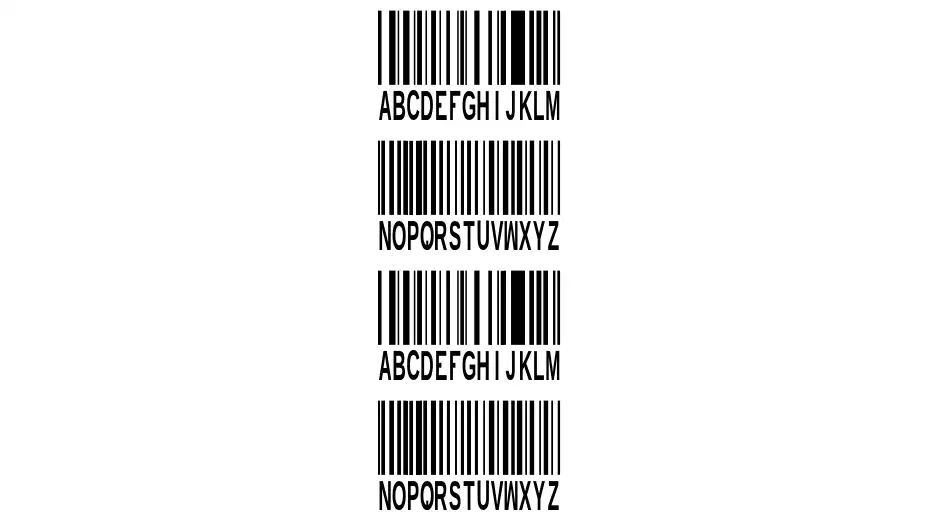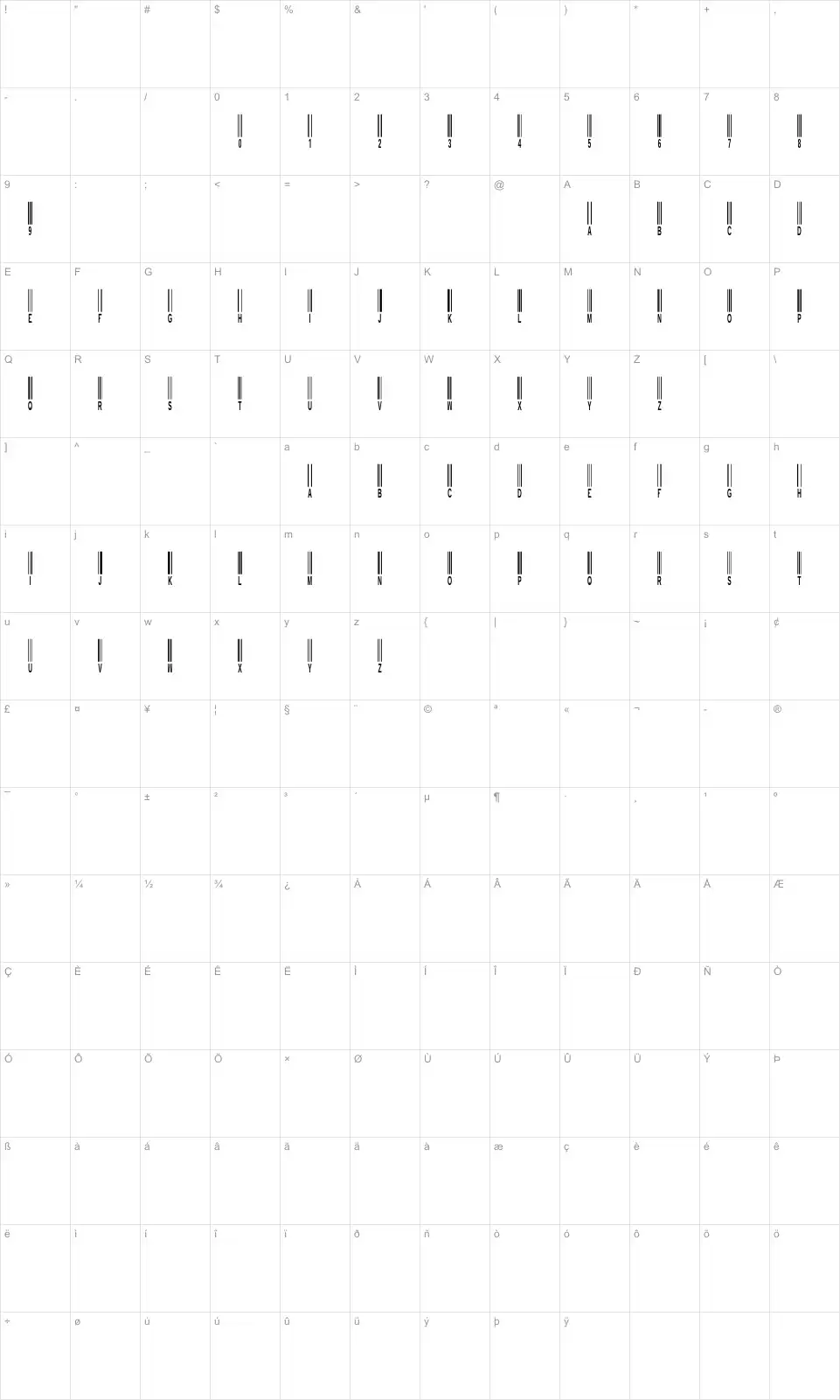
A fonte ‘New Barcode Font TFB’, criada pelo designer kaiserzharkhan, é uma opção única para quem deseja incorporar um elemento visual distintivo a seus projetos. Esta font pertence à categoria de Dingbats e foi adicionada à nossa biblioteca em 12 de julho de 2022. Com um tamanho de apenas 4 KB, ‘New Barcode Font TFB’ é uma opção compacta e eficaz para incorporar barcodes em qualquer projeto, seja ele um logo, um site, ou até mesmo em um projeto de design gráfico. Para quem está considerando usar esta font, o designer disponibiliza uma opção para baixar diretamente o arquivo fonte ou gerar um visual personalizado de texto online. Esta funcionalidade permite que os usuários vejam como a font se adaptará a diferentes textos antes de utilizá-la. Com a licença de uso gratuito para fins pessoais, ‘New Barcode Font TFB’ torna-se um recurso indispensável para qualquer designer ou criador de conteúdo que queira adicionar um toque único e moderno a seu trabalho.